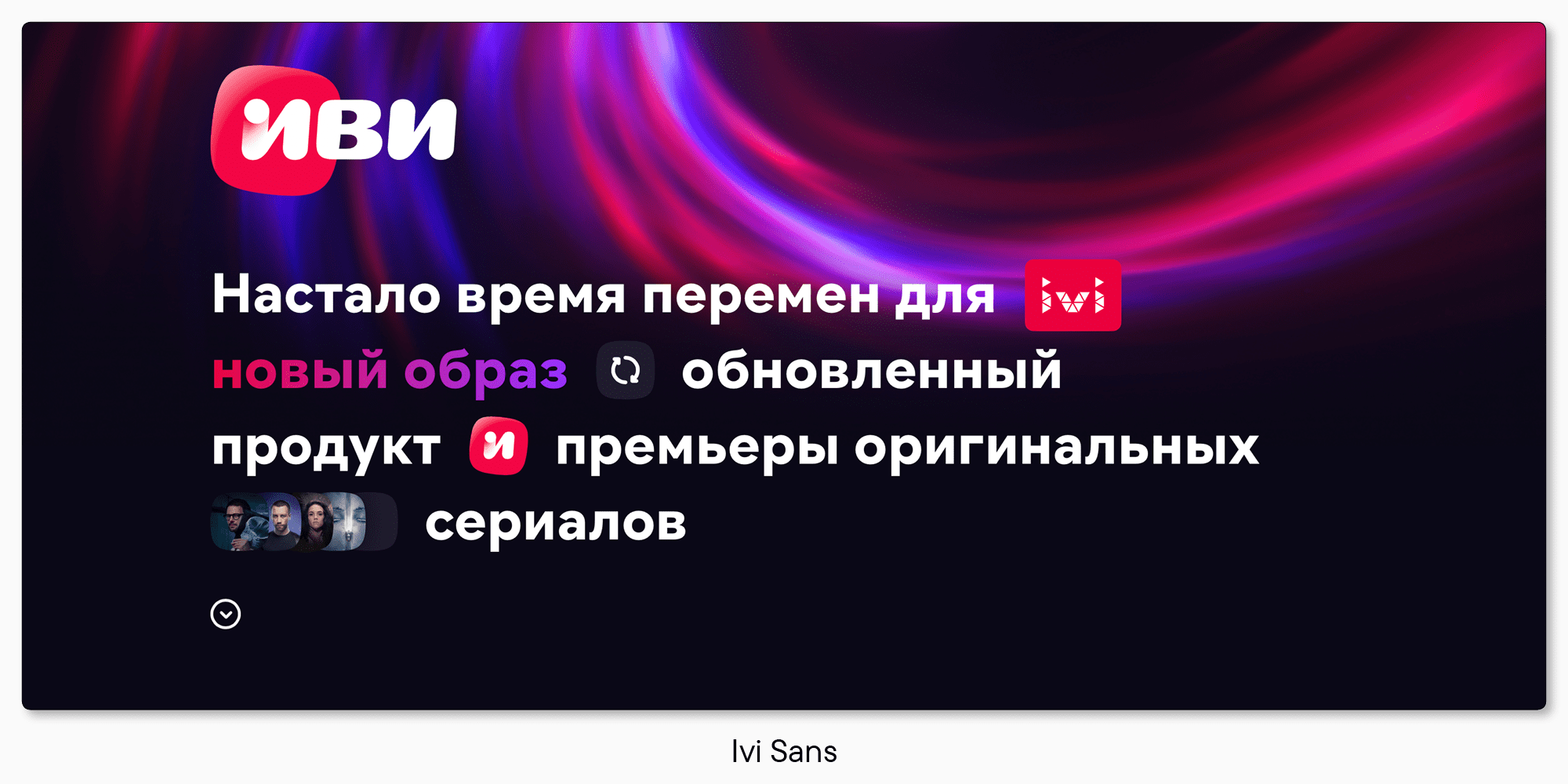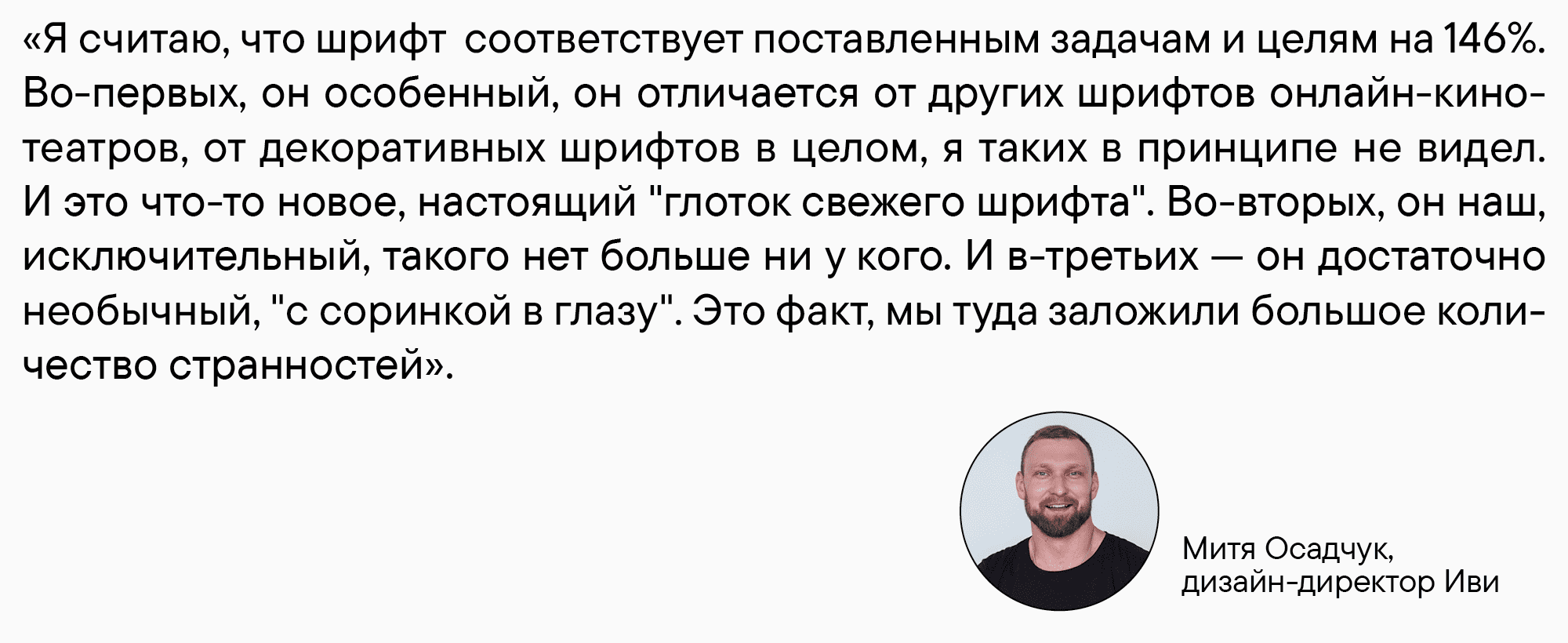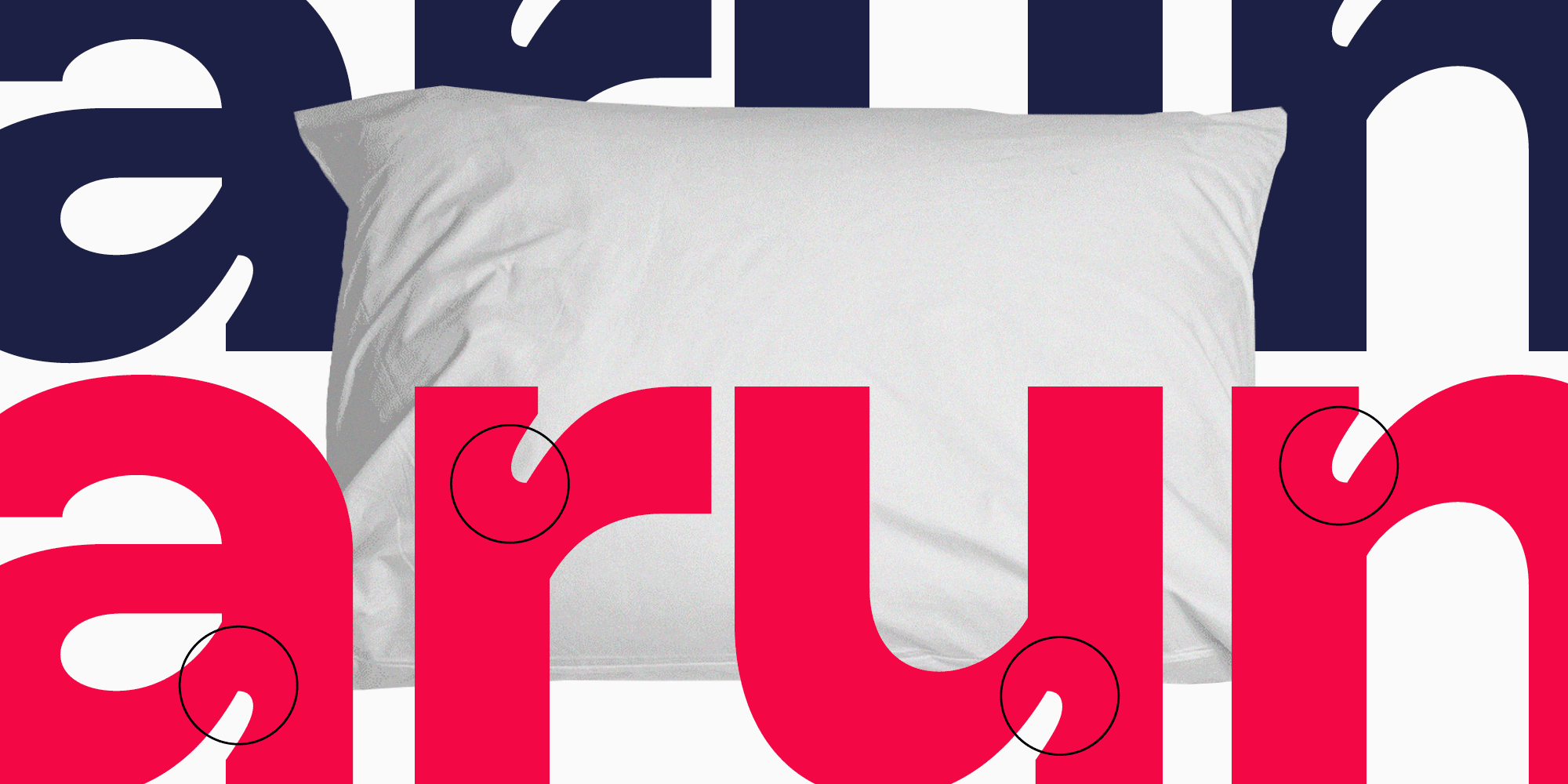
Кино и буквы: как создавался фирменный шрифт для онлайн-кинотеатра Иви
В 2022 году популярный онлайн-кинотеатр Иви провел ребрендинг. Сейчас компания активно работает над тем, чтобы все точки контакта с аудиторией соответствовали эмоциям, заложенным в платформу бренда. Для Иви важно доносить новые ценности через все составляющие айдентики — не только через логотип, но и через внешние коммуникации, цвет, стиль иллюстраций, tone of voice и в том числе шрифт.
В поисках фирменного шрифта команда Иви обратилась за помощью к нам — студии TypeType. И после всех обсуждений, брейнстормов, ресерчей и зарисовок мы создали его — Ivi Sans Display, который станет новым фирменным шрифтом онлайн-кинотеатра.
Из этой статьи вы узнаете о том, как и зачем он создавался — от первых скетчей и исследований до проработки деталей и фич. И, конечно, увидите, что получилось в результате! О процессе расскажут дизайн-лид TypeType Антонина Жулькова, дизайн-директор Иви Митя Осадчук и руководитель отдела исследований Иви Евгения Савельева.
Итак — камера, мотор, поехали!
Завязка: недостающий фрагмент
Когда наше сотрудничество только началось, ни у кого еще не было четкого плана действий. После ребрендинга вся визуальная айдентика бренда стала более мягкой и дружелюбной, острые треугольники в логотипе сменились на округлые формы. Но шрифт остался прежним: для всех коммуникаций использовался базовый геометрический гротеск Ivi Sans.
Основная загвоздка заключалась в том, что он хорошо подходил для цифрового продукта — был технологичным, удобочитаемым, хорошо смотрелся на экранах, — но совершенно не соответствовал новому стилю и ценностям компании. У него не было характера и харизмы. Поэтому команда Иви решила, что в рамках ребрендинга нужно найти и новый шрифт.
Так у компании появился запрос — создать гарнитуру, которая станет голосом бренда. Было важно, чтобы шрифт стал яркой деталью фирменного стиля и сам по себе ассоциировался с Иви.
С таким запросом команда онлайн-кинотеатра и обратилась в TypeType. Почему именно к нам? Митя рассказал об этом (и нам очень приятно от таких слов!).
Мы предложили три варианта сотрудничества. Первый — доработать Ivi Sans: сделать для него дополнительное начертание, чтобы он стал более акцентным. Второй — сделать шрифт, который будет хорошо работать в паре с существующим: перенести большую часть элементов, но, опять же, сделать его более акцидентным. И третий — сделать что-то совершенно новое, полноценный фирменный шрифт, соответствующий новому стилю.
В итоге вместе с командой Иви мы решили пойти именно третьим путем и не ориентироваться на существующий шрифт. Так начались поиски нового «голоса» Иви — будущего Ivi Sans Display.
Развитие действия: творческие поиски и «научный подход»
Итак, нам нужно было создать шрифт, который будет соответствовать шести прилагательным, определяющим ценности Иви: эмоциональный, современный, мягкий, оригинальный, яркий и добрый. Эти определения стали опорными точками в работе. Было еще два менее важных, но дающих дополнительные ориентиры слова: асимметричный и странный. Также основной упор нужно было делать на кириллице, чтобы она получилась яркой и интересной, так как вся коммуникация происходит на русском языке.
Наши дизайнеры предложили несколько вариантов скетчей. И здесь в игру вступил отдел исследований Иви: чтобы понять, куда двигаться дальше, исследование провели в двух этапах.
Для начала нужно было понять, какой эмоциональный отклик рождают разные шрифты. То есть, во-первых, какой из вариантов скетчей больше всего соответствует ценностям бренда, во-вторых — важен ли вообще характер шрифта для пользователей, отличается ли эмоциональное восприятие разных вариантов. Специалисты Иви взяли четыре новых шрифта, разработанных TypeType, и сравнили с текущим шрифтом онлайн-кинотеатра. Ivi Sans стал «точкой ноль», которая помогла понять, насколько необычные шрифты отличаются от нейтральных в восприятии пользователей.
Исследователи провели опрос — каждый шрифт оценивали по 100 человек, которых попросили отметить, насколько предложенный шрифт соответствует тем или иным качествам. Каждый респондент видел только один шрифт, то есть шрифты не сравнивали между собой. Результаты показали, что реакция действительно отличается. Эмоциональное восприятие новых шрифтов было гораздо ярче, чем восприятие стандартного варианта.
После этого начался второй этап исследования. Выбранный по результатам первого этапа шрифт сравнили со шрифтом конкурентной площадки. Нужно было сопоставить эмоциональный отклик и читабельность этих двух шрифтов. Так мы поняли, что удобочитаемость — еще одна важная характеристика, которую необходимо было учитывать в дальнейшей работе.